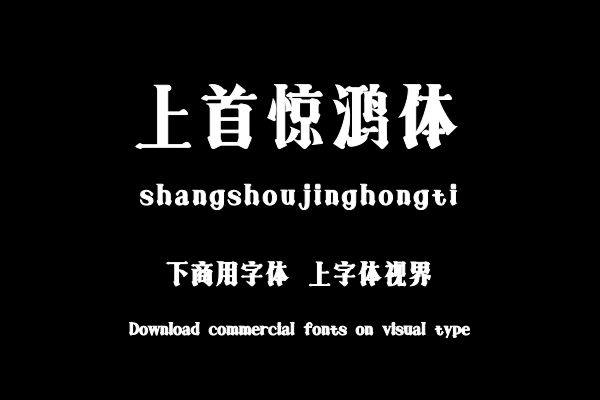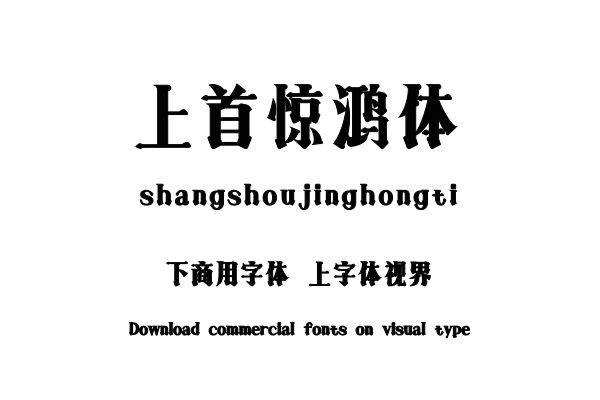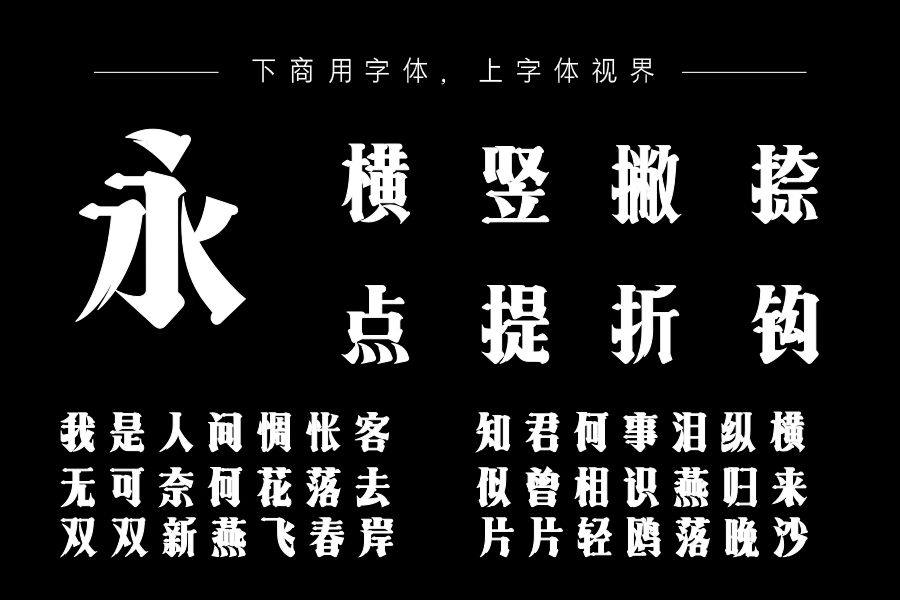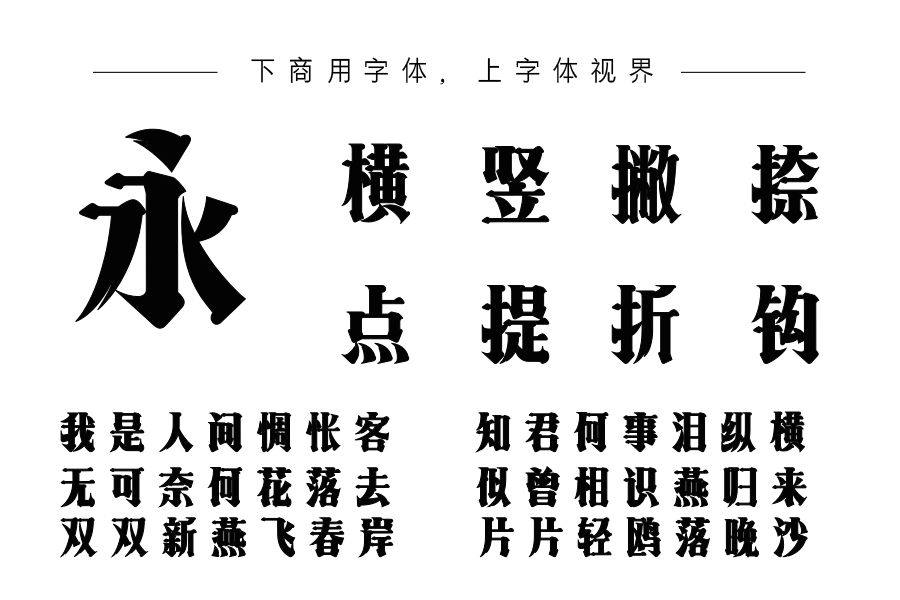
上首惊鸿体,字体末端的字脚明显,在粗细变化的同时,能保证格调和视觉形象的协调。字体特点鲜明,艺术感十足。购买须知:“下载服务费”与“字体VIP”所获得字体 仅用于个人非商用, 商用请联系付费授权。本字体为电脑用字,手机没有root权限不支持直接手机换字(手机如何root,请自行百度搜索教程)。购买前请先 了解清楚后再付款 ,字体为虚拟产品无法回收 一旦购买不支持退款。